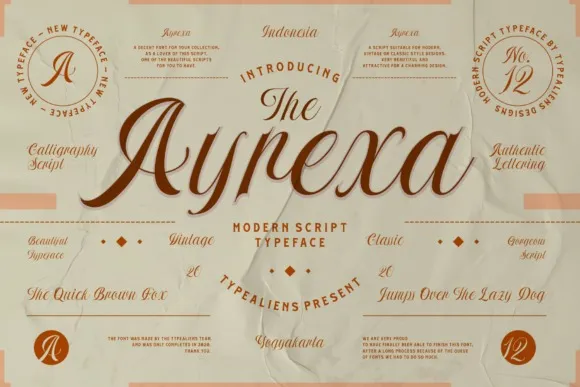
A Ayrexa Font é uma elegante tipografia círconflexual inspirada nos designs tipográficos retro icônicos. Ela foi criada por um designer chamado typealiens, e seu estilo único cria ligaturas incrivelmente atraentes que tornam ela perfeita para o design de convites de casamento ou qualquer projeto que necessite de uma aparência sofisticada. Seu charme elegante e sua complexidade em linhas curvas fazem dela uma escolha ideal para designers que desejam dar um toque sofisticado aos seus projetos. Com uma paleta única de ligaturas, a Ayrexa Font adiciona um toque especial ao seu design, tornando-a perfeita para aqueles procurando por algo elegante e minimalista no mesmo tempo.